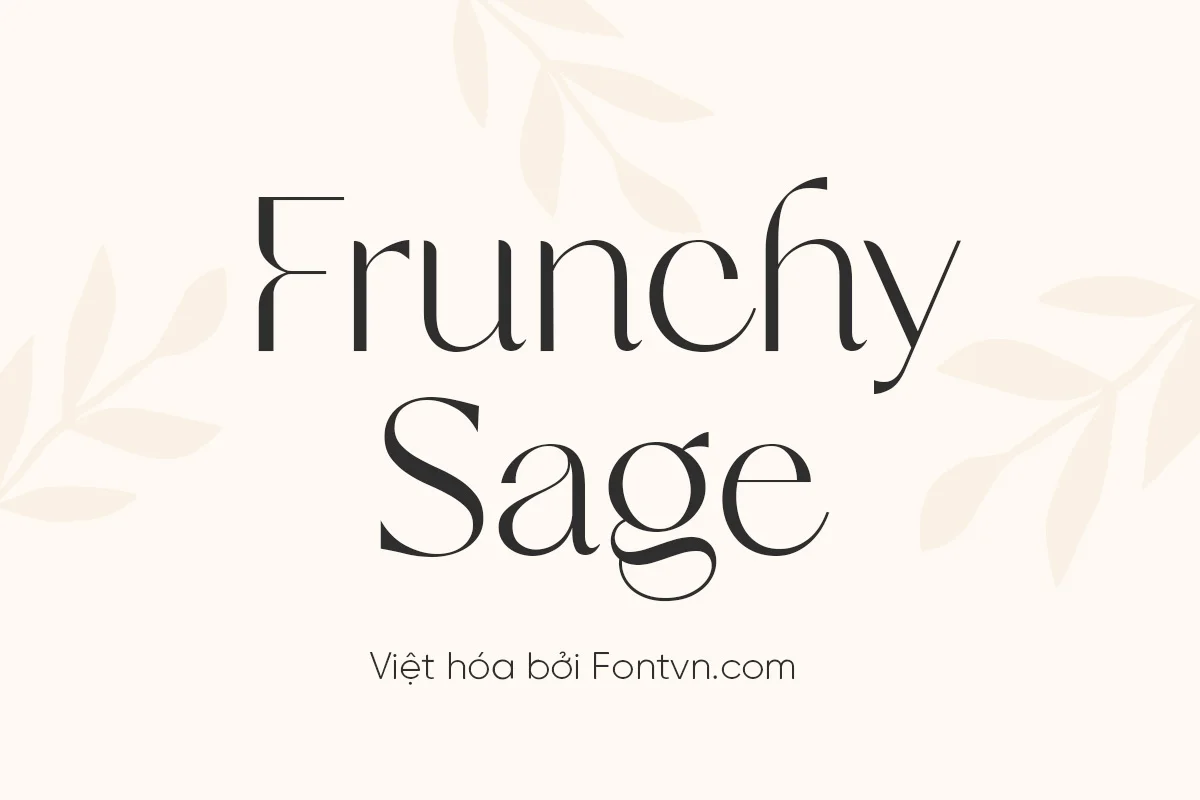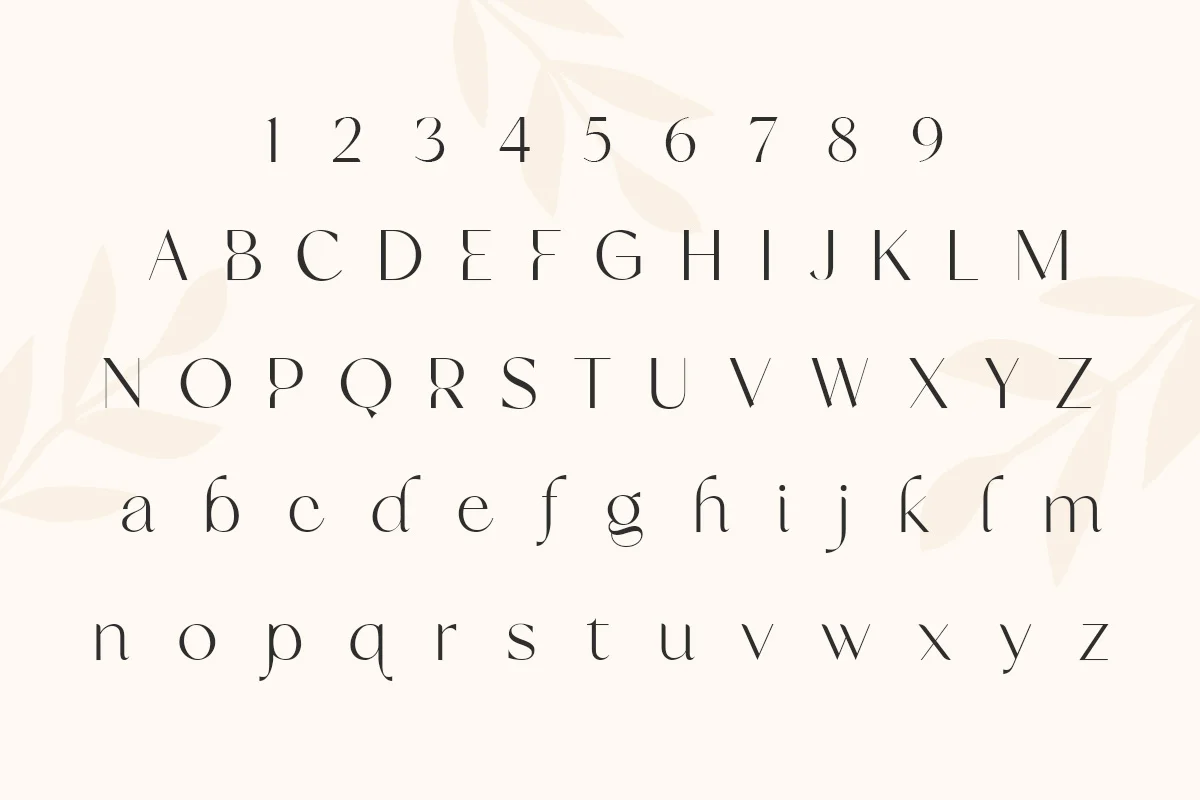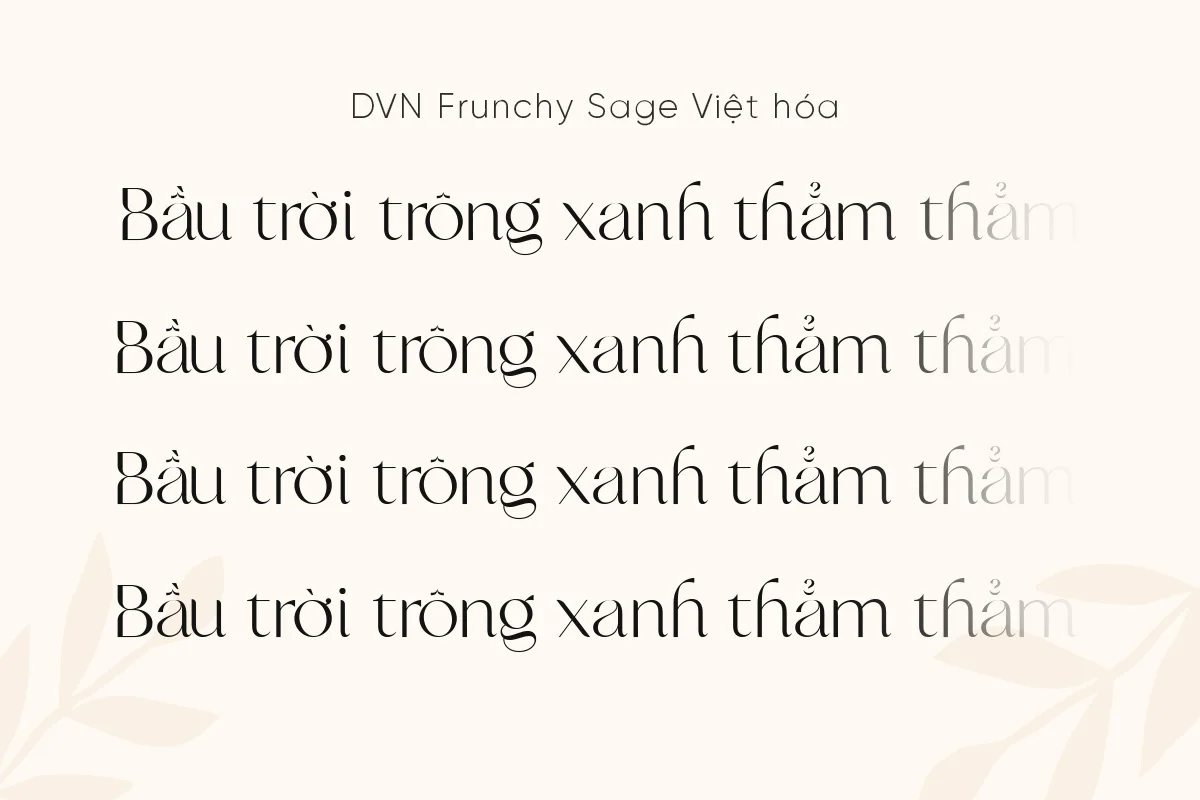
Frunchy Sage là một kiểu chữ serif hiện đại mang đậm phong cách thời trang cao cấp, với những đường cong tinh tế và chi tiết sắc sảo. Font sở hữu sự cân bằng hoàn hảo giữa vẻ đẹp cổ điển và sự phá cách đương đại, thể hiện rõ qua các chi tiết như chân chữ thanh mảnh, cấu trúc chữ mở thoáng và những ký tự đặc biệt như “g” hay “y” được tạo hình uốn lượn đầy nghệ thuật.
Với phong thái thanh lịch nhưng không kém phần cá tính, Frunchy Sage lý tưởng cho các thiết kế liên quan đến thời trang, mỹ phẩm, thương hiệu cao cấp, bìa tạp chí, hay các tiêu đề nổi bật trên mạng xã hội.
Điều đặc biệt là Frunchy Sage cũng được xem như một trong những font chữ kinh điển trên nền tảng Canva, được rất nhiều nhà thiết kế sử dụng để tạo ra các sản phẩm có tính thẩm mỹ cao mà vẫn dễ tiếp cận. Sự xuất hiện thường xuyên của nó trong các template Canva chuyên nghiệp chứng minh sức hút bền vững và tính ứng dụng đa dạng của font này.
Frunchy Sage không chỉ là một font chữ – nó là tuyên ngôn về phong cách.
Với phong thái thanh lịch nhưng không kém phần cá tính, Frunchy Sage lý tưởng cho các thiết kế liên quan đến thời trang, mỹ phẩm, thương hiệu cao cấp, bìa tạp chí, hay các tiêu đề nổi bật trên mạng xã hội.
Điều đặc biệt là Frunchy Sage cũng được xem như một trong những font chữ kinh điển trên nền tảng Canva, được rất nhiều nhà thiết kế sử dụng để tạo ra các sản phẩm có tính thẩm mỹ cao mà vẫn dễ tiếp cận. Sự xuất hiện thường xuyên của nó trong các template Canva chuyên nghiệp chứng minh sức hút bền vững và tính ứng dụng đa dạng của font này.
Frunchy Sage không chỉ là một font chữ – nó là tuyên ngôn về phong cách.